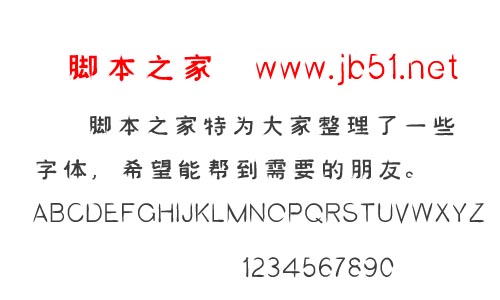
邯鄲禿廢體是邯鄲字庫推出的一款個性藝術(shù)字體,非常有意思,風格比一般的字體更有特色,連貫字跡顯得干練而不凌亂,清新簡明,具有很好的視覺感,適合應(yīng)用于藝術(shù)設(shè)計、平面宣傳設(shè)計、網(wǎng)頁設(shè)計,書法字帖等領(lǐng)域,歡迎喜歡邯鄲禿廢體的朋友前來下載使用。